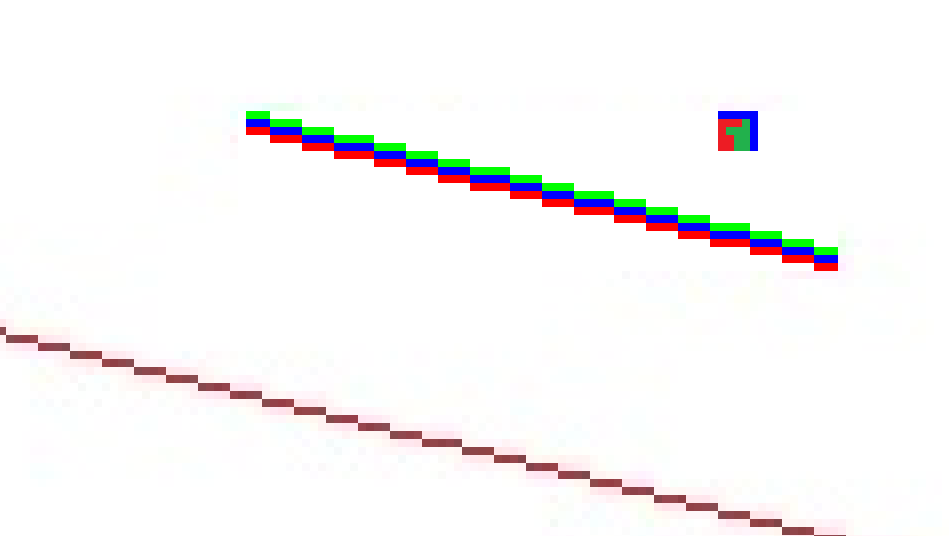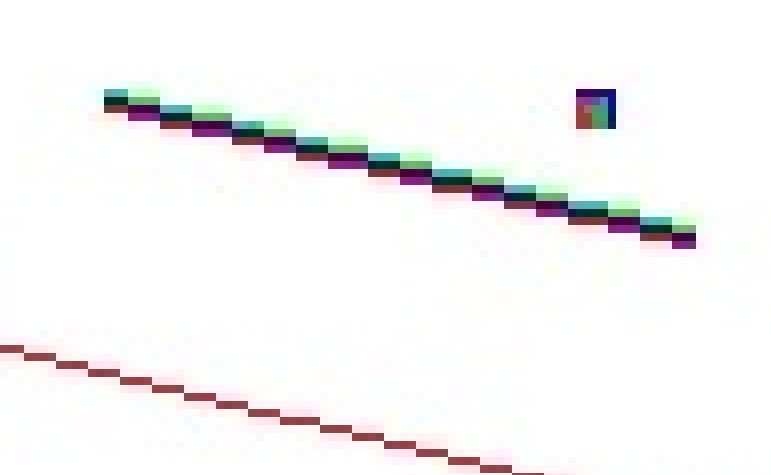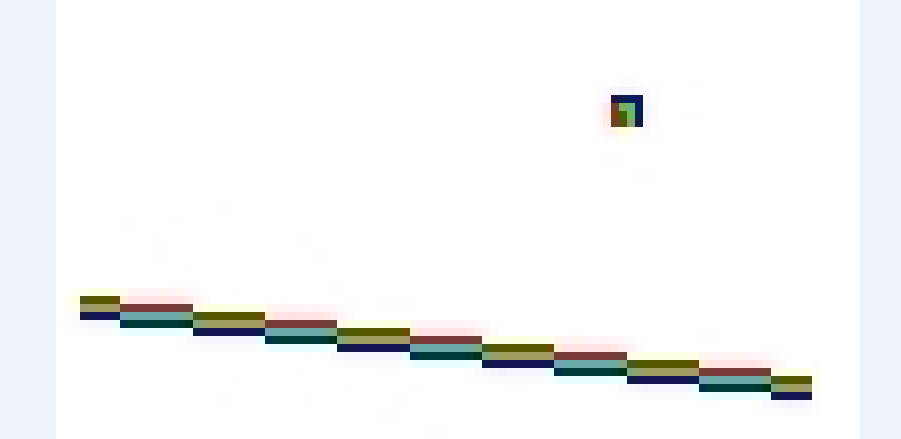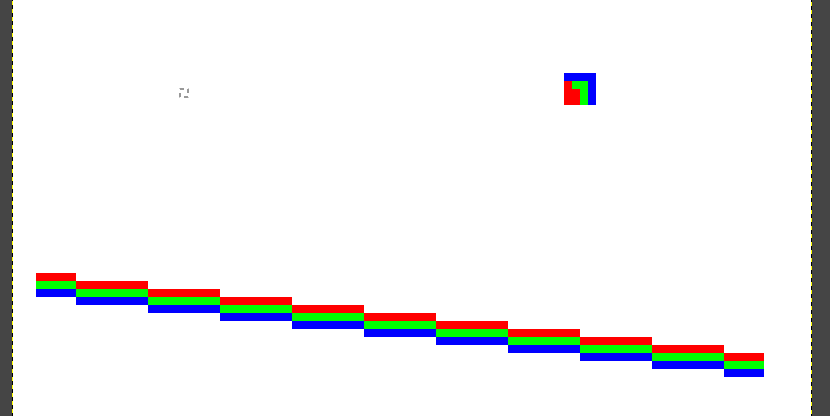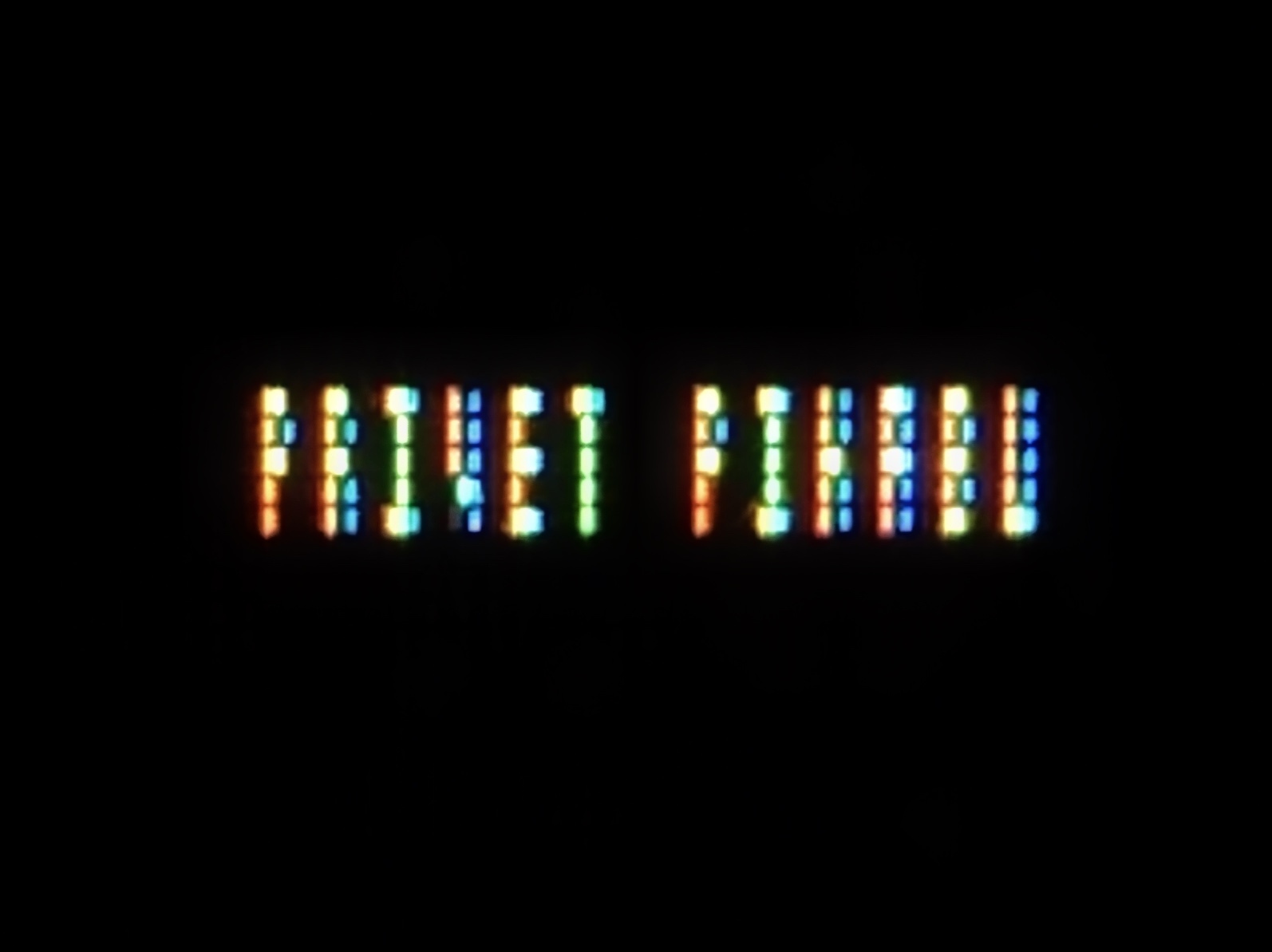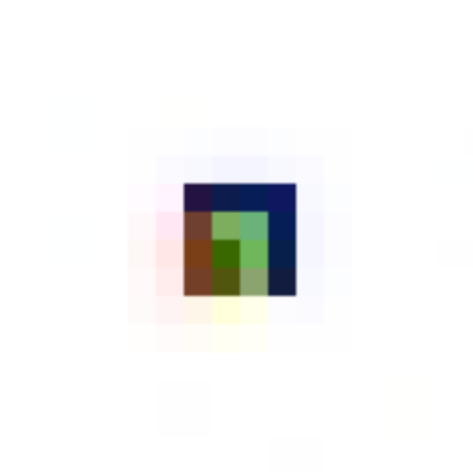
Субпиксельный шрифт⁠⁠
Все мы знаем, что изображение на мониторе состоит из пикселей. А пиксель в свою очередь из субпикселей трех цветов: красного, зеленого и синего. Теперь приготовтесь стать настоящими киношными хакерами или шпионами и посмотрите на эту картинку.
Какие-то невнятные полосочки размером с муравья. Давайте посмотрим поближе:
Вы уже должно быть думаете "Sannori, ты с ума сошел?". Но нет. Нам нужно проникнуть еще ближе!
И отправляемся мы на субпиксельный уровень! Да, там нам не нужны дороги. Возьмите свой телефон или фотоаппарат, включите макрорежим и сфотографируйте максимально близко первую картинку этого поста.
Вот это поворот. Да, читаемый шрифт толщиной в один пиксель это реальность. Практическое применение этому можно придумать самому. К примеру, использовать как подпись на своих рисунках или фотографиях. Или оставлять как послание для тех, кто знает об этом шрифте.
Так, как шрифт цветной, его нельзя просто добавить в операционную систему. Сообщение составлено путём копипаста отдельных буковок из специального алфавита-шаблона. Он на картинке ниже в красном прямоугольнике. Справа пояснение к нему. Закидываем в редактор, максимально приближаем левые столбики и составляем из них своё сообщение.
Шрифт называется Millitext, его оригинальный автор Matt Sarnoff. Сообщение составлял я, снимал на айфон. Полученная вами фотография может отличаться от моей. Ни одного монитора в процессе написания поста не пострадало.